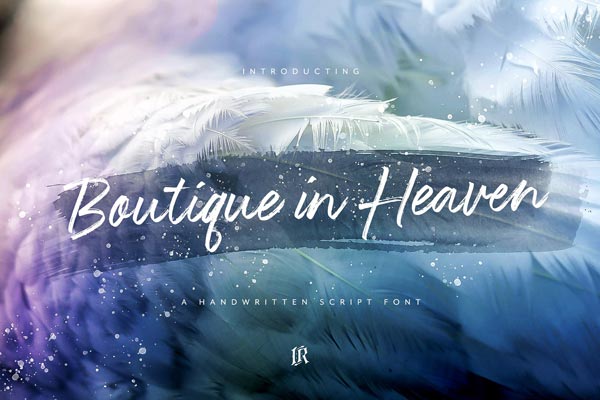
Boutique – بوتیک در بهشت نام یک فونت چند زبانه، جذاب و فوق العاده حرفه ای است که توسط Rosenberg طراحی شده و در Creative Market با قیمت 16 دلار بفروش میرسد. این قلم زیبا مناسب برای طراحی انواع تیشرت، مجلات، رسانه های اجتماعی، منو رستوران ها، کارت پستال، دعوت نامه، طراحی هدر و بسیار از طرح ها و پروژه های گرافیکی و تحت وب نیز میباشد که نسخه نهایی آن بصورت کامل و البته رایگان هم اکنون از نال اکس آماده دانلود و استفاده میباشد.
ویژگی های فونت :
- طراحی دقیق و کاملا حرفه ای
- نمایش بی نقص تمامی حروف و اعداد بدون مشکل
- مناسب برای انواع طرح های گرافیکی
- مناسب برای ساخت و طراحی فونت، پوستر، لیبل و …
بوتیک در بهشت فونت قلم مو گسسته با پشتیبانی چند زبانه است. ایده آل برای تی شرت، مجلات، پوشش تلفن، رسانه های اجتماعی، منوهای رستوران، کارت پستال، دعوت نامه، عروسی، هدر و بسیاری دیگر است. این فونت قلم با مجموعه ای کامل از حروف کوچک و بزرگ، طیف وسیعی از لیگاچارهای نقطه گذاری، اعداد، متغیرهای کوچک و پشتیبانی چند زبانه همراه است.